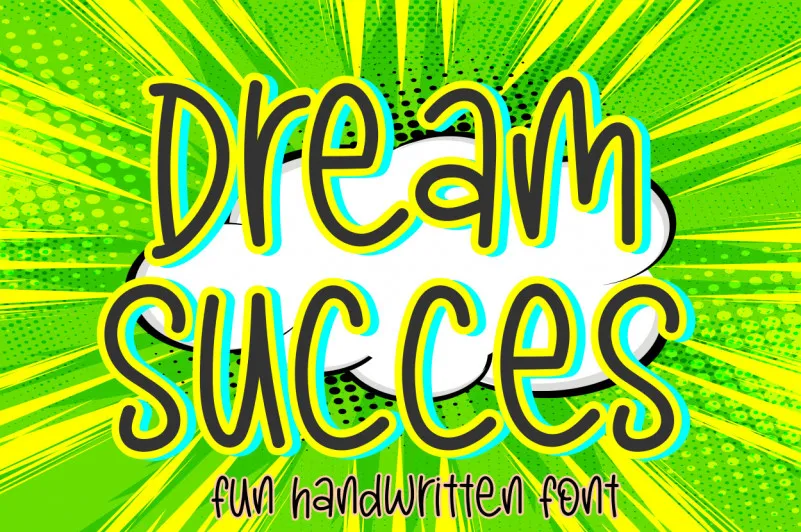
Dream Succes Font
Esta é uma fonte à mão escrita que combina leitura legível com naturalidade. Perfeita tanto para criações infantis, quanto para designs relacionados a bonecos ou jogos para crianças. Seja qualquer projeto que necessite de um toque de delicadeza e encanto, essa fonte é uma escolha incrível. Ideal para adicionar um toque único em elementos gráficos infantis ou em projetos de arte digitais inspiradas em histórias animadas. A sugiharto1790 criou uma fonte que traz vida à sua criação, tornando-a mais amável e divertida. Não perca esta fonte excepcional para seu próximo projeto gráfico, ela certamente fará a diferença no resultado final.
Designer: sugiharto1790